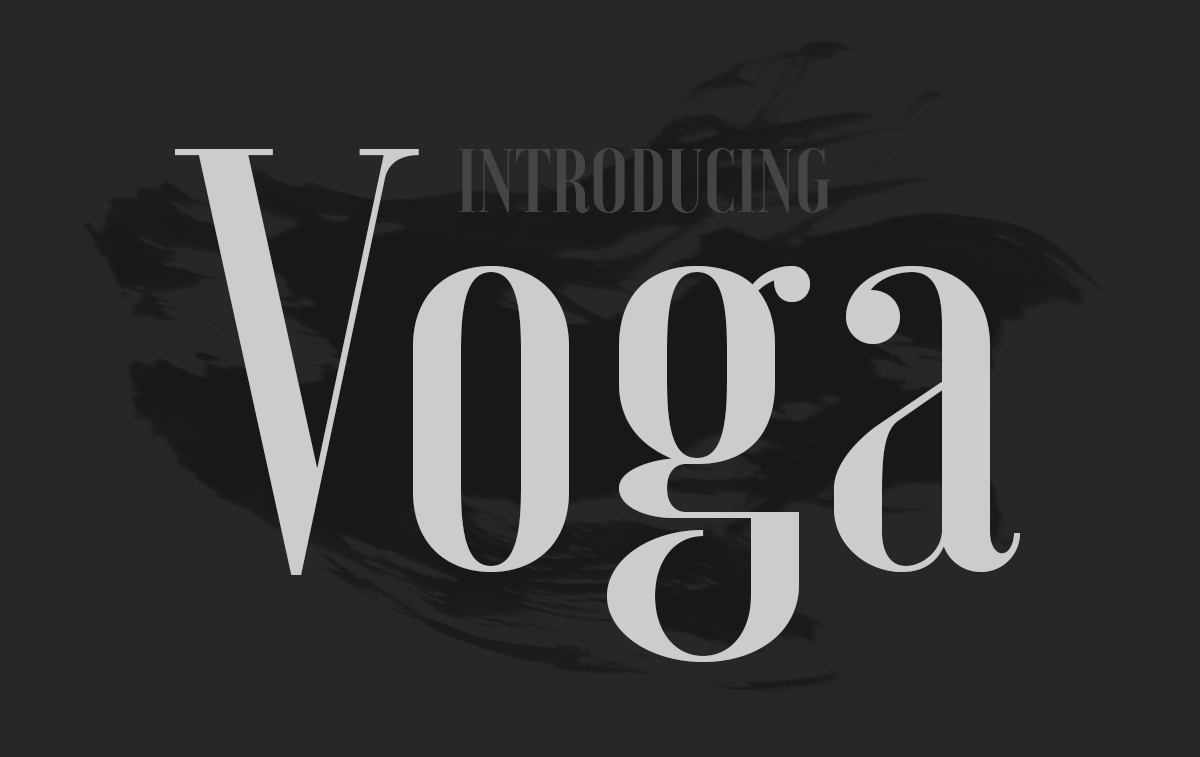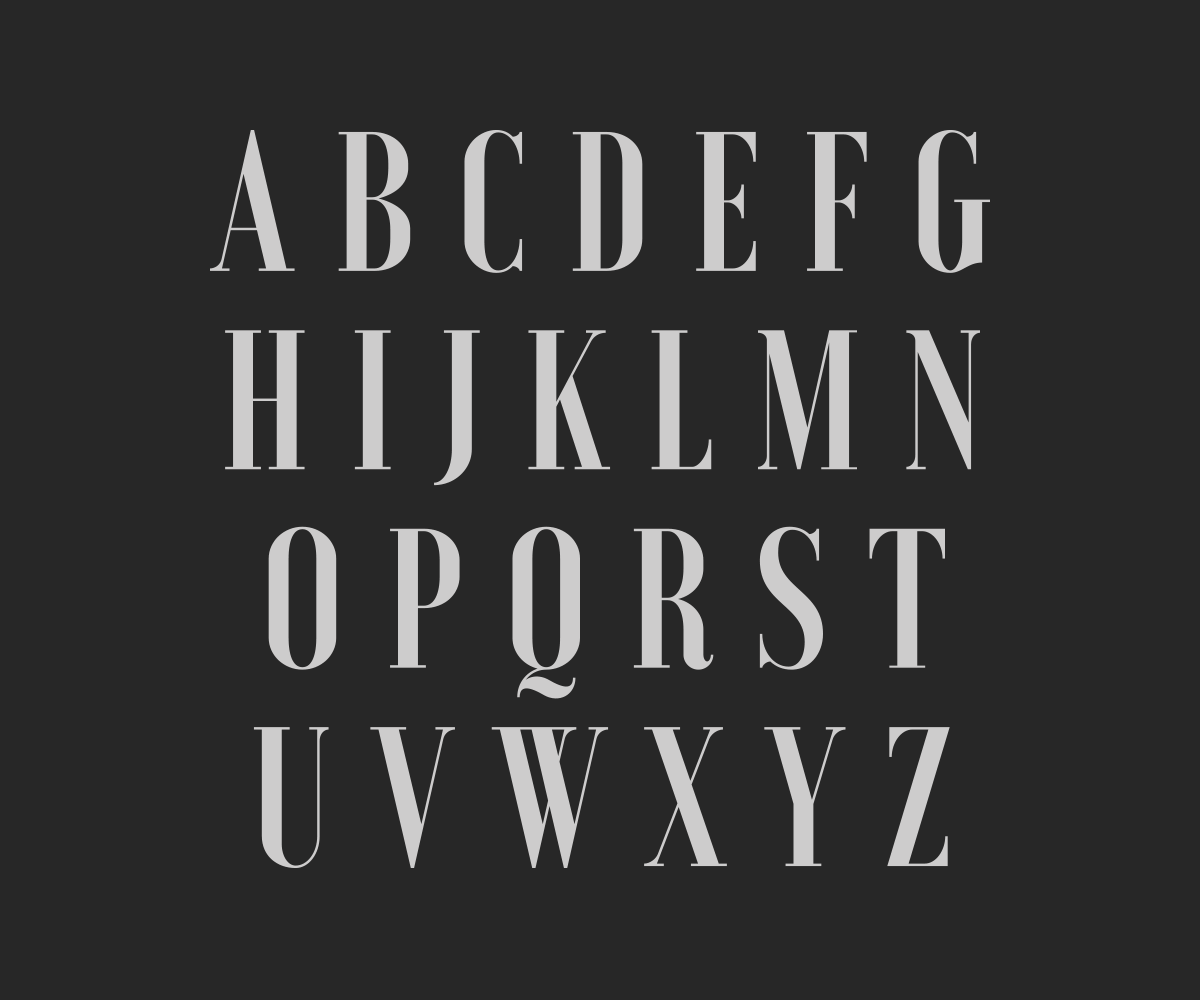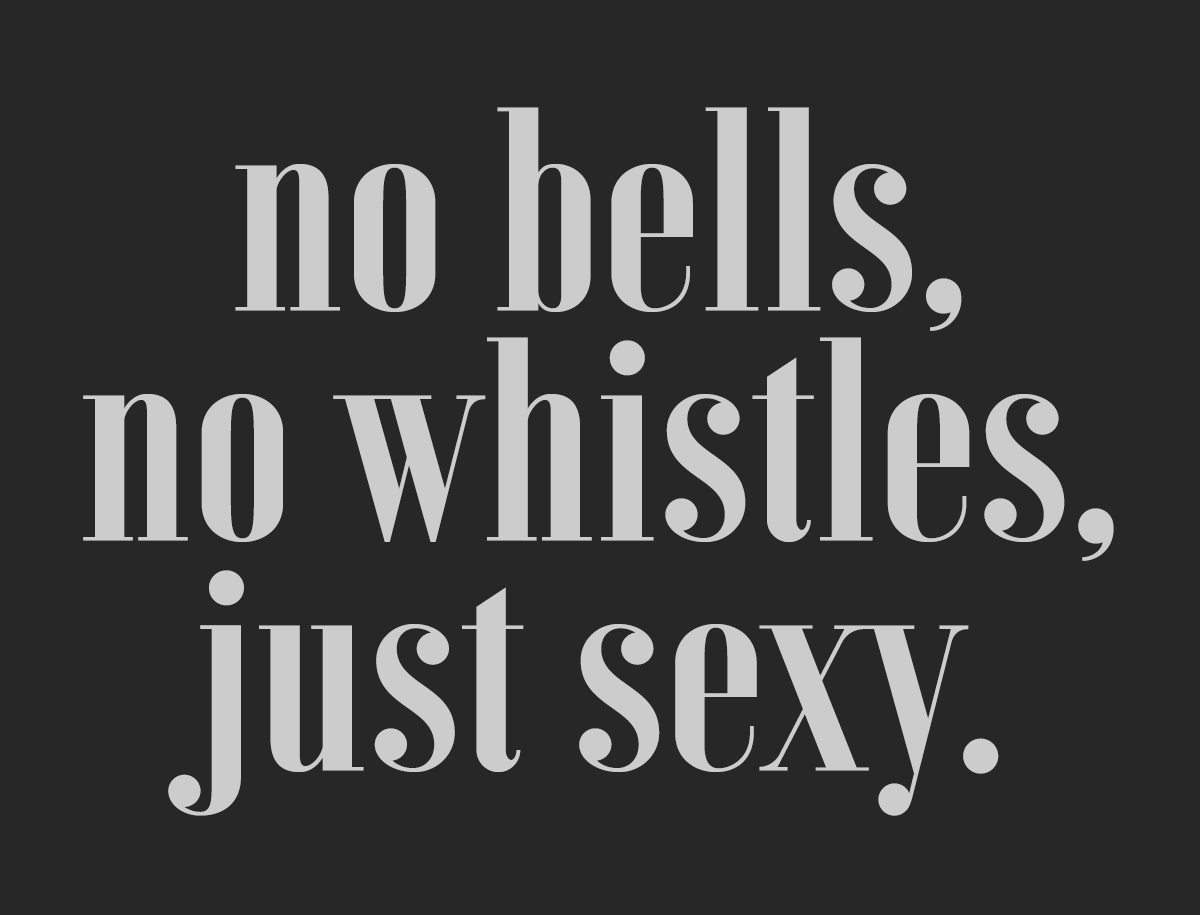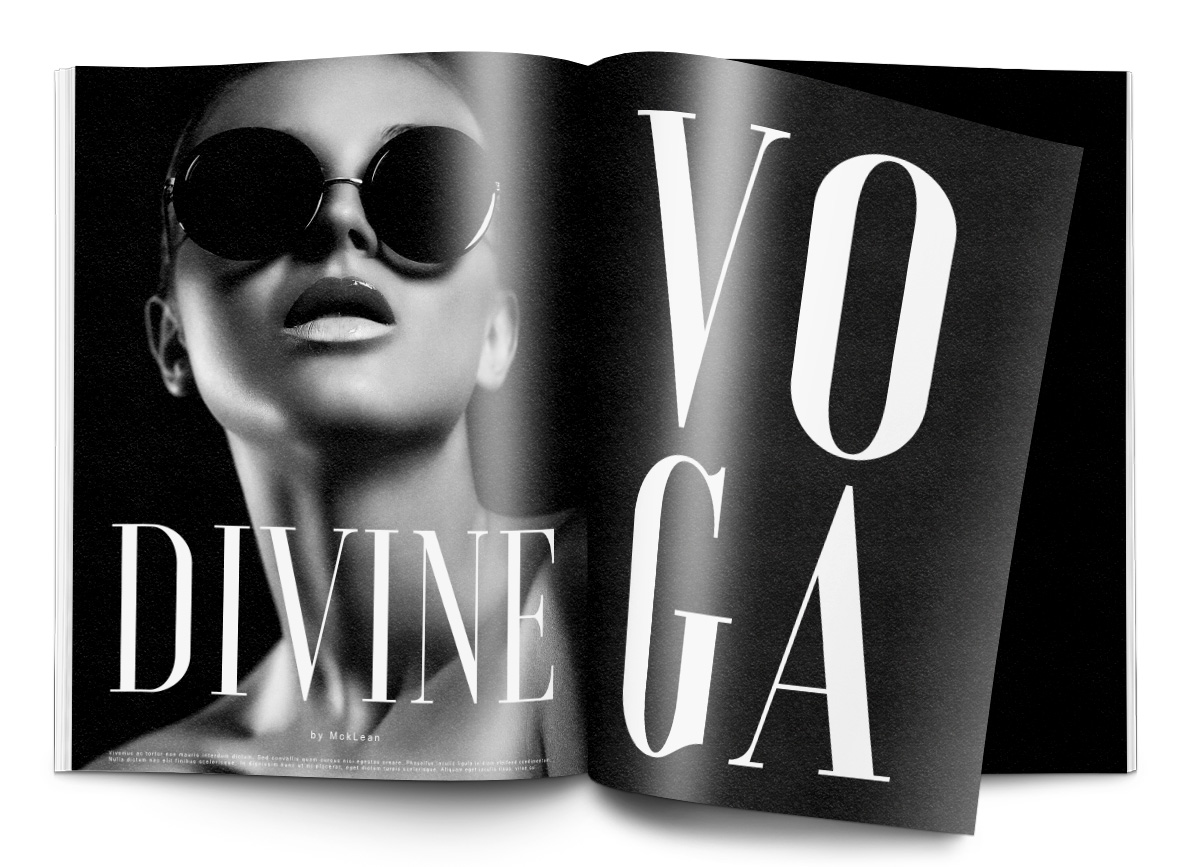
El turno de hoy es para Voga. Una tipografía moderna, elegante y sexy. Con curvas y fuertes lineas rectas, perfecta para titulos y selecciones de tipografía grande. Voga esta inspirada en tipografías icónicas como Bodoni y Didot. Gracias al diseñador Canadiense Charles Daoud.